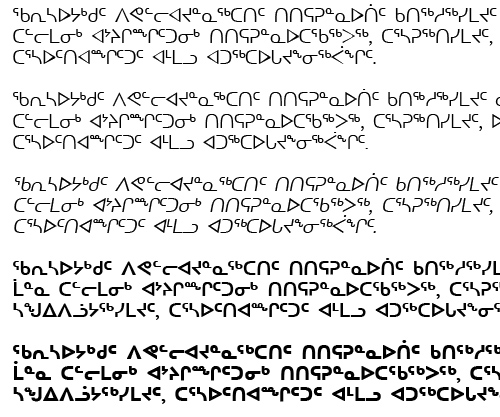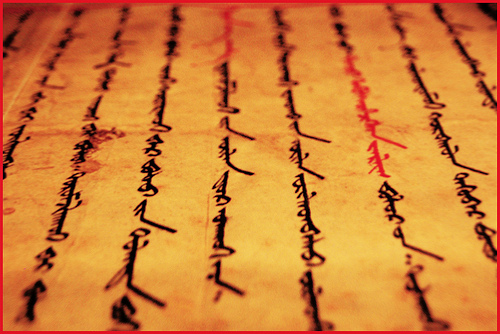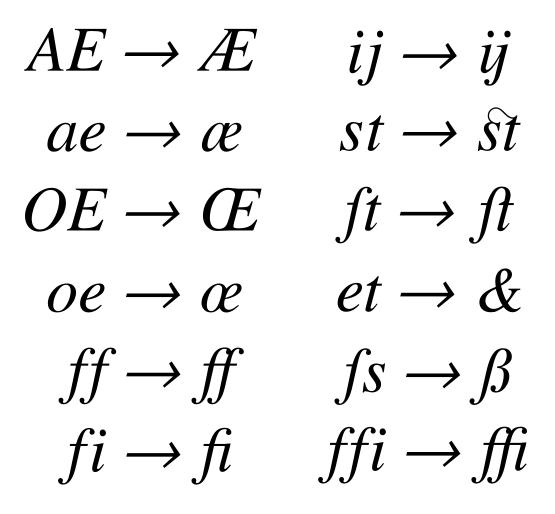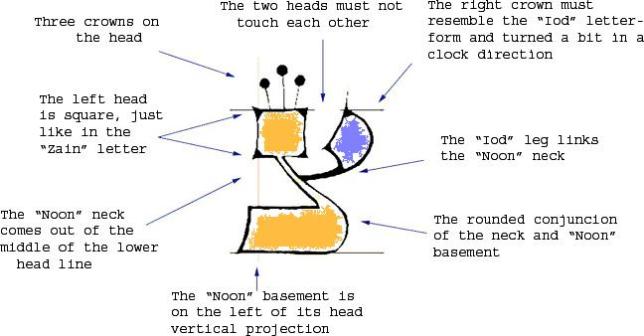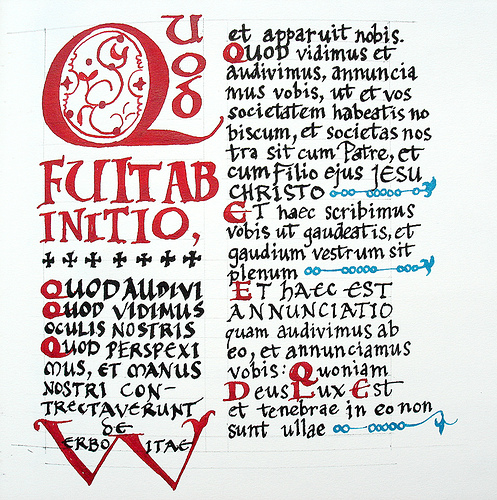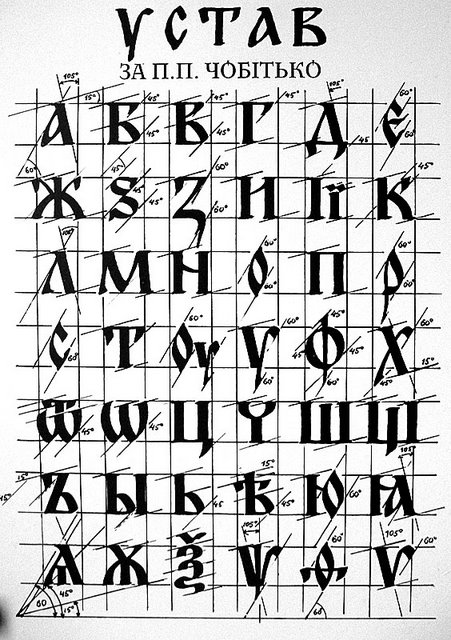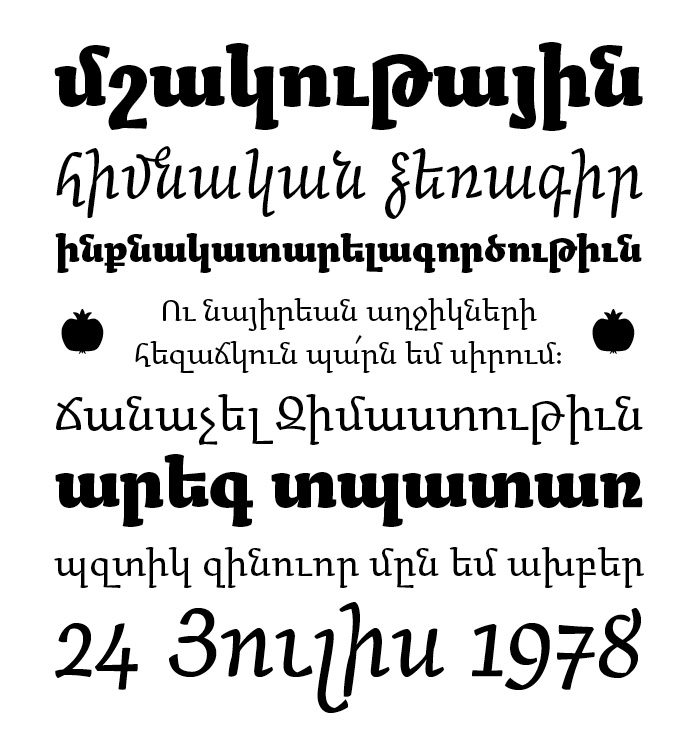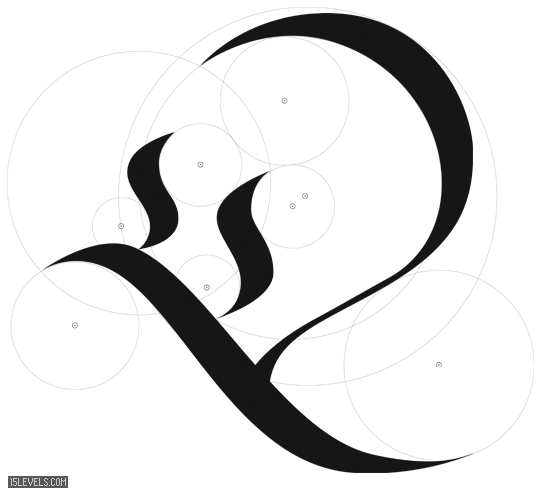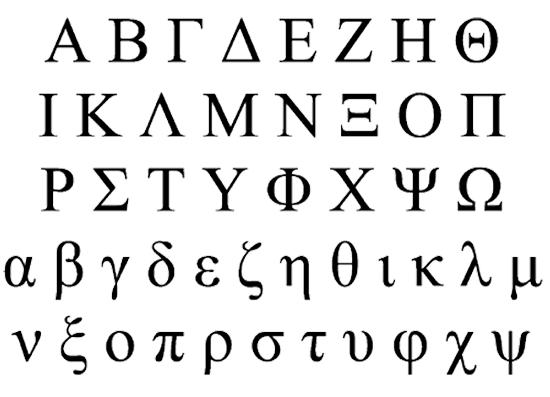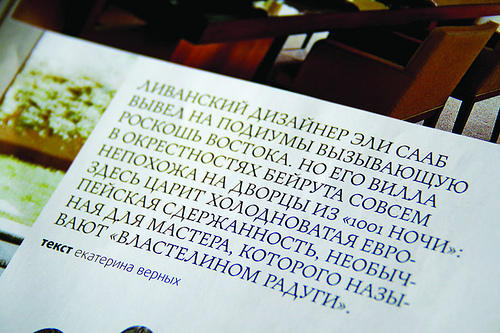
La Belleza de la tipografía: Sistemas de escritura y Caligrafía de alrededor del mundo II
La belleza de los sistemas de escritura es que cada uno tiene algo único de lo cual obtener inspiración. Hace unos meses, en la primer parte de este artículo, cubrimos los lenguajes: Árabe, de extremo oriente (chino, japonés, coreano y vietnamita) y unas cuantas escrituras Índicas (Devanagari, thai y tibetano).
Ahora regresamos para la segunda (y última) parte, la cual es un poco diferente pero igual de interesante. Verás que algunos de las características de los lenguajes presentados aquí  claramente se corresponden a nuestro sistema basado en el latín, mientras que otros son muy poco familiares. El punto de esta segunda parte es completar nuestro recorrido a los sistemas de escrito de alrededor del mundo y pensar más generalmente de lo que significan. Cubriremos los siguientes:
• Hebreo
• Escrituras europeas modernas (Latín, Griego, Cirílico, Armenio, Georgiano)
• Mongol
• Inuktitut
• Alfabeto fonético internacional
Sistemas de escritura del mundo.
Antes de que empecemos, tomemos un momento para entender como todo encaja:
Estimar de cuantos idiomas son hablados en el mundo es difícil, pero se calculan alrededor de 7000 lenguajes y dialectos, con cientos de sistemas para escribirlos. Afortunadamente los principales sistemas de escritura caen en cuatro grandes categorías:
• Alfabéticos
Como probablemente ya sabrás, un alfabeto es un sistema de escritura segmentado en el cual un grupo estandarizado de letras (grafemas) tiene un equivalente fonético. La palabra alfabeto deriva del «alpha» y «beta», las primeras dos letras del alfabeto griego. Hay dos tipos importantes de clasificaciones en este sistema:
• Adbjad, los  cuales contiene símbolos solo para las consonantes, u opcionalmente vocales escritas como diacríticos ( ej. el árabe y el hebreo)
• Abugida, aquellos cuyos signos básicos denotan consonantes con vocales inherentes. Vocales seguidas aparte de las inherentes son marcadas con marcas diacríticas u otras modificaciones sistemáticas de las consonantes (ej. Devanagari).
• Logografías
En un sistema logogrífico, cada carácter (logograma) representa  una sola palabra gramatical y es más precisa que un morfema (ej. Chino).
• Silabarios
Como el nombre lo sugiere, en un sistema silábico, los caracteres representan o aproximan silabas (o más precisamente «moras»), los cuales componen las palabras. Un símbolo típicamente representa una consonante seguida de una vocal, o una vocal sola (ej Japonés).
• Característicos
Un sistema de escritura característico representa detalles más finos que un alfabeto. Cada símbolo representa no un fonema completo, sino características fonéticas que componen un fonema, como pronunciación y lugares de articulación. (ej. Coreano).
Desafortunadamente para nosotros, muchos de los sistemas de escritura no pueden ser clasificados como solamente de un tipo. Muchos lenguajes incluyen varias de estas características. En el inglés, por ejemplo, es difícil que las agrupaciones de letras fonéticas igualen los sonidos.
Fin del paréntesis. Podría continuar, pero esto no sería el artículo por el que han estado esperando. Así que regresando a nuestro tema, exploraremos la belleza tipográfica de varios lenguajes. Si estás interesado en esta fascinante clasificación de sistemas de escrituras, la Wikipedia es un buen comienzo.
Hebreo
El alfabeto hebreo es un descendiente del alfabeto arameo, el cual a su vez es descendiente del alfabeto fenicio. Como el árabe, el alfabeto hebreo es un abajad es su forma tradicional ( un alfabeto consistente solo de consonantes), se escribe de derecha a izquierda. Tiene 22 letras, 5 de las cuales tiene formas diferentes al final de una palabra (llamadas «sofit»). El hebreo es un alfabeto que carece de letras «mayúsculas», también se le llama al alfabeto debido a las dos primeras letras.
Diacríticos
Nuevamente al igual que el árabe, la ortografía hebrea moderna incluye varios tipos de diacríticos como ayuda a la pronunciación. Estos se escriben encima, abajo o dentro de las letras, de tal manera que no se altere el espacio de la línea. El texto que contiene estas marcas se le llama texto «puntuado» y contiene tres tipos de marcas
• Los niqqud (puntos) son los más usados. representan vocales o son usados para distinguir entre las pronunciaciones alternativas de varias letras del alfabeto.
• Los geresh (Inicialismos indicativos) y los gershayim (acrónimos indicativos) son diacríticos que afectan la pronunciación. Son también usados para denotar numerales pero no son considerados parte de los niqqud.
• Las cantilaciones son acentos que muestran como los pasajes bíblicos deben de ser cantados y algunas veces funcionan como puntuaciones..
Letras en negro, puntos en rojo y cantilación en azul.